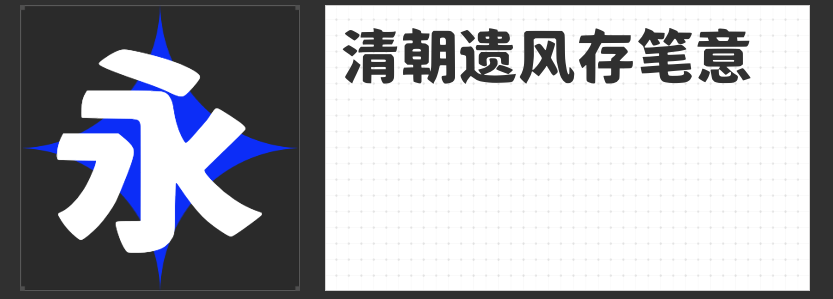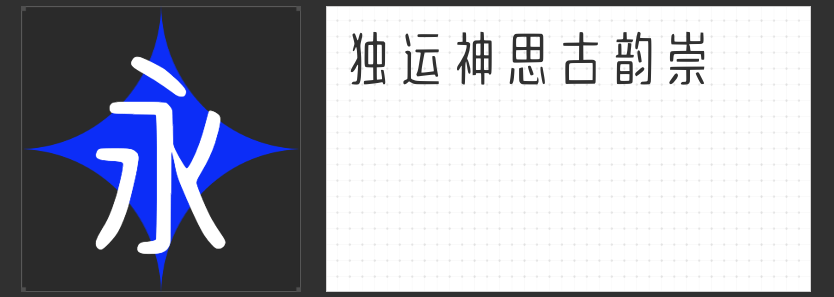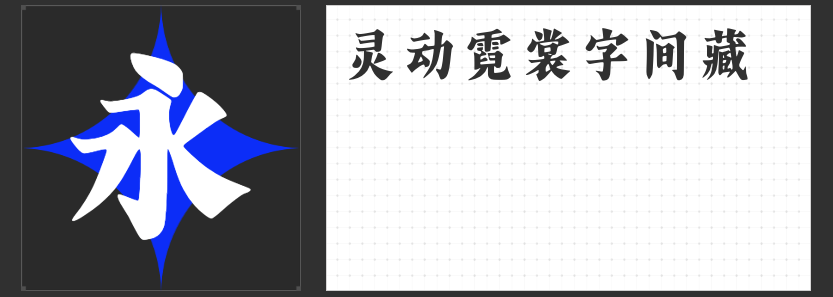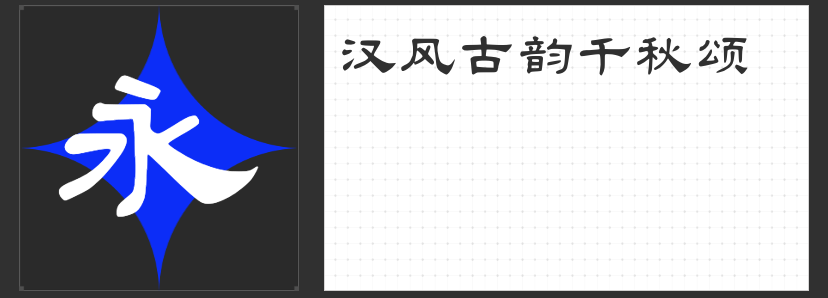
“小欣大萌”品牌字体推荐:穿越古今的雅致韵味
在浩如烟海的字体世界中,总能找到几款触动心灵的独特设计。今天,为大家推荐的是“小欣大萌”品牌的四款字体,它们各具特色,不仅展现了古典文化的魅力,还融入了现代设计的精髓。
1.大萌汉:古风今韵的端庄雅致
“大萌汉”字体以古隶体为蓝本,通过现代设计的巧思,使得这款字体在保留古风古韵的同时,更显得端庄与雅致。无论是用于书籍封面还是广告设计,都能瞬间吸引眼球,让人感受到一股来自古代的文化气息。
2.大萌明:刚柔并济的舞者之姿
“大萌明”字体借鉴了明朝字体的特点,整体修长而笔划结构独特。每个字都如同一位舞者,在纸面上翩翩起舞。有的矫健有力,如刚猛的战士;有的则轻盈柔美,似温柔的少女。这种刚与柔的交织,使得“大萌明”字体独具魅力,令人陶醉其中。
3.大萌秦:古典韵味与现代阅读的完美融合
“大萌秦”字体以秦朝小篆为基础,融入了现代字型的元素。它保留了小篆的古典韵味,又符合现代人的阅读习惯。这种设计不仅让字体易看易懂,更在无形中传递着一种跨越千年的文化力量。
4.大萌清:跨越时空的民国风韵
“大萌清”字体则带我们回到了清朝与民国时期。在宣纸轻展的柔光里,这款字体与民国风韵交织成一幅跨越时空的画卷。无论是用于怀旧风格的文案还是历史题材的书籍装帧,“大萌清”都能完美诠释那份独特的韵味。
这四款“小欣大萌”品牌的字体来自励字造梦共创字库,每一款都承载着不同的文化底蕴和审美价值。它们不仅是文字的载体,更是连接古今、传递文化的重要桥梁。快来选择一款你喜欢的字体,为你的作品增添一份独特的雅致韵味吧!